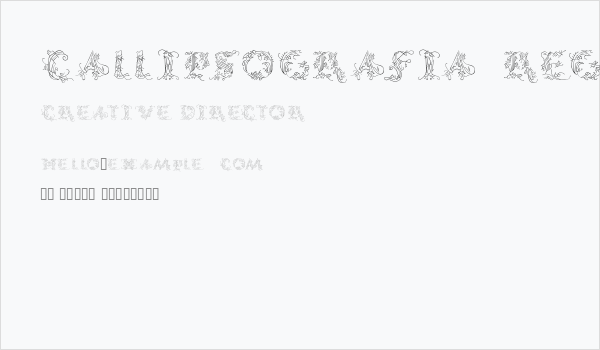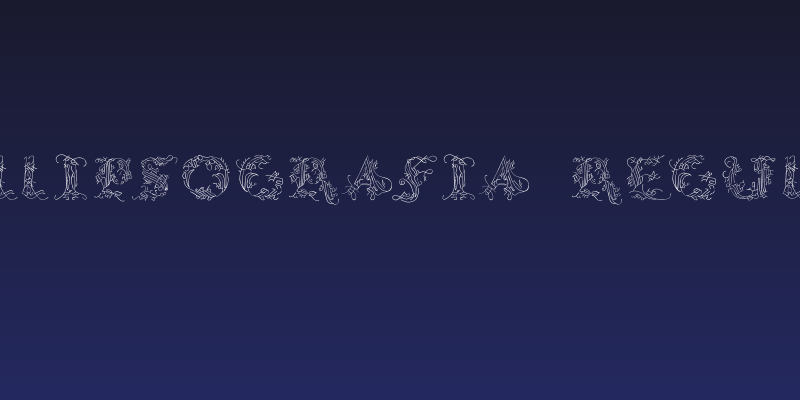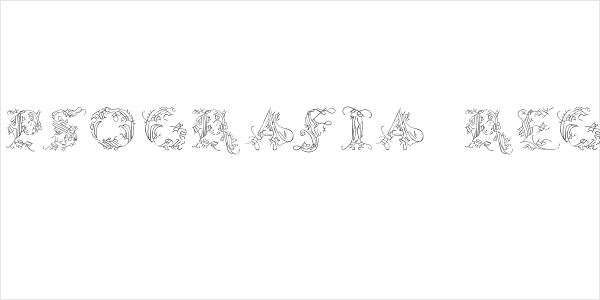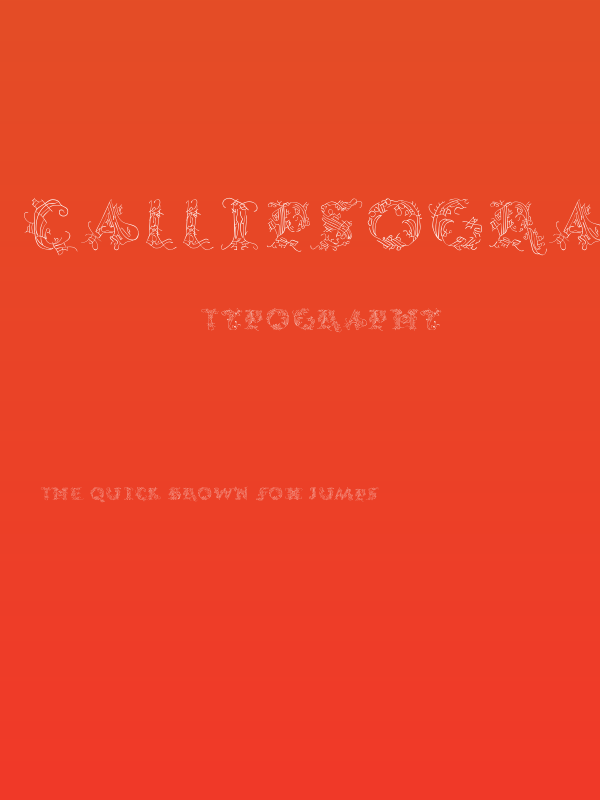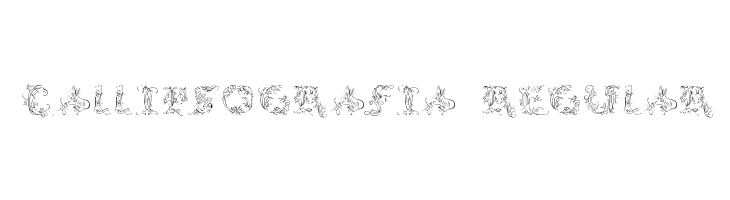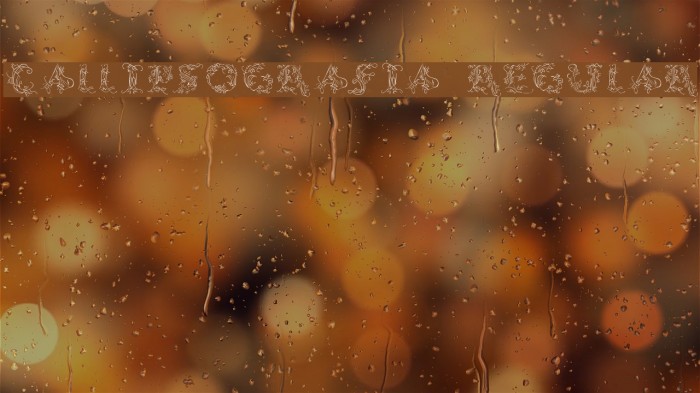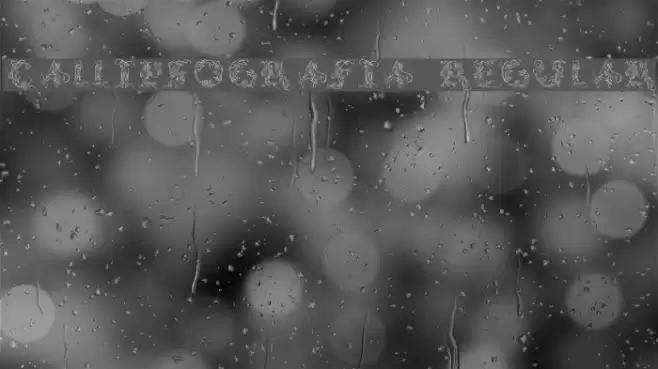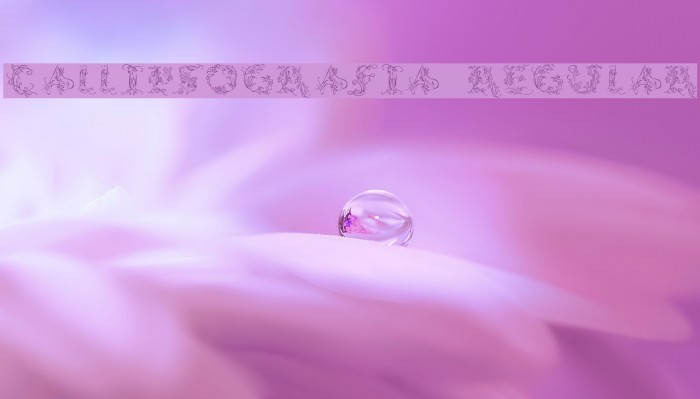
CalliPsoGrafia Regular Font
| Stil general | Vintage, Decorative |
| Caz de utilizare | Headlines, Artistic projects, Invitations |
| Proiecte propuse | Ideal for wedding invitations, greeting cards, artistic posters, and branding materials that require a touch of elegance and sophistication. |